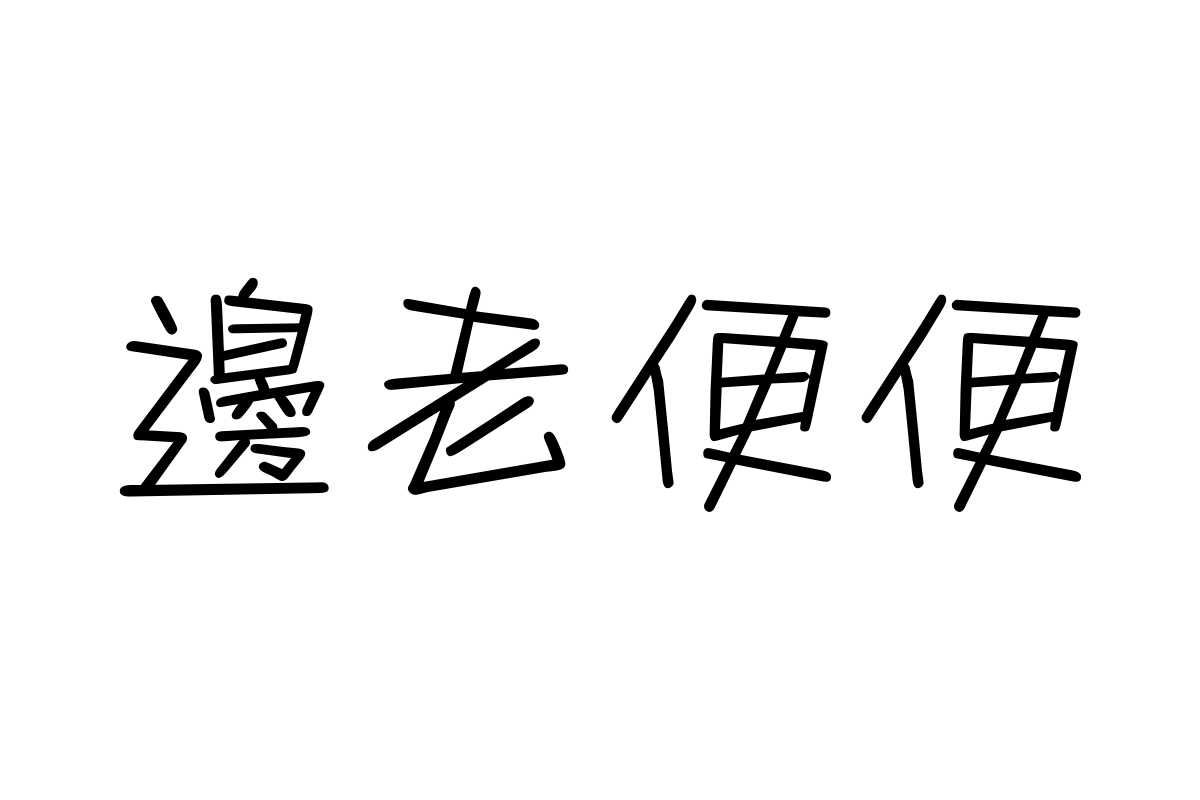
汉仪丫丫体繁是一套适用于中文排版的字体,具有独特的艺术风格和设计。它由汉仪字库出品,是一款非常受欢迎的字体。
汉仪丫丫体的字形结构独特,笔画流畅,给人一种优雅的感觉。它的线条粗细适中,既有力度又不失柔和,适合用于各种类型的文本,如标题、正文、广告等。
汉仪丫丫体的字体大小多样,从小到大都有,可以满足不同场合的需求。此外,它还具有多种字重和行距设置,可以根据需要进行个性化调整,以适应不同的排版需求。
汉仪丫丫体还具有一定的可读性,即使在较小的屏幕上也能清晰阅读。它的间距和行距设计合理,使得整体视觉效果更加协调。
总的来说,汉仪丫丫体繁是一款非常实用的中文字体,无论是在商业还是日常生活中,都能发挥出其独特的魅力。